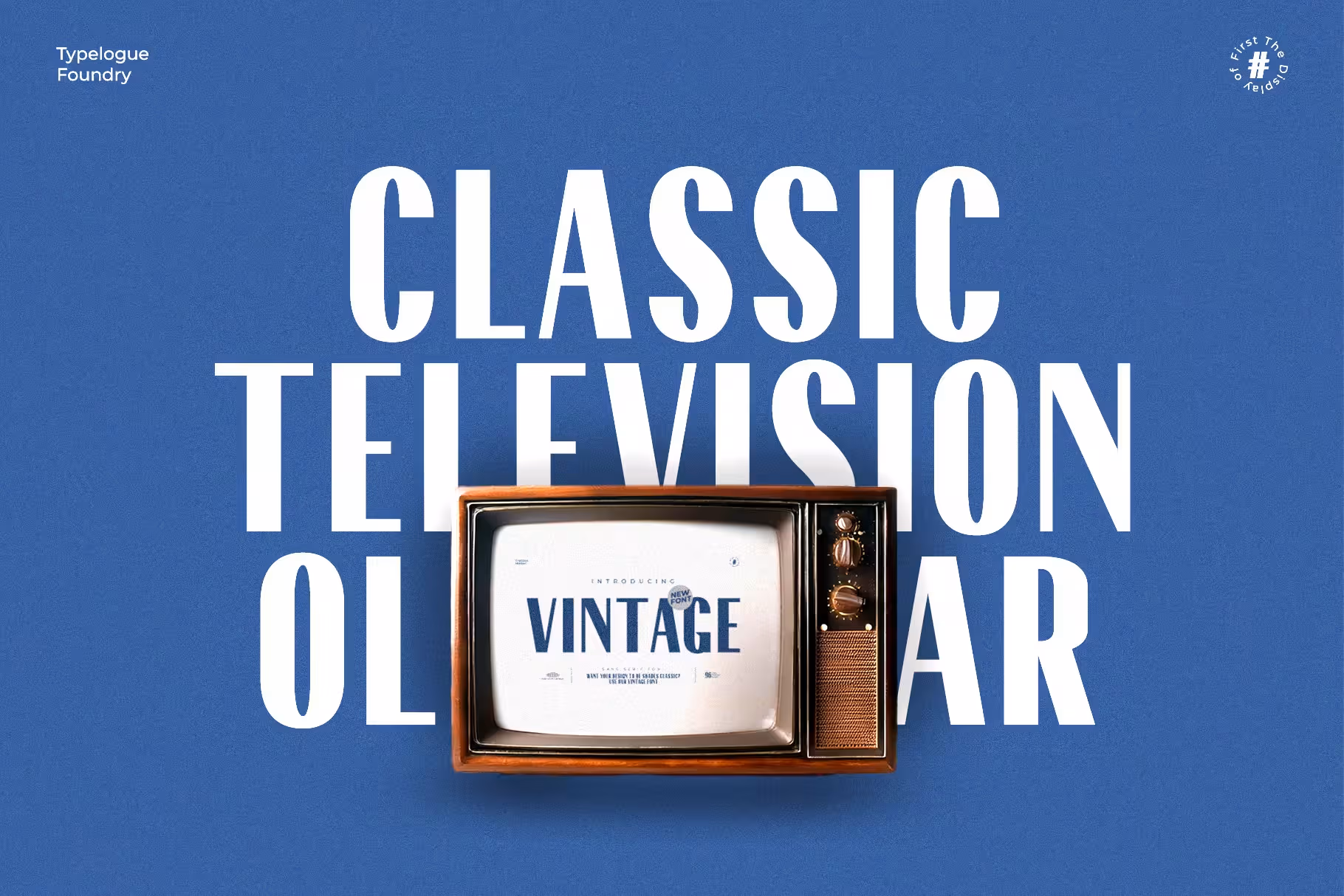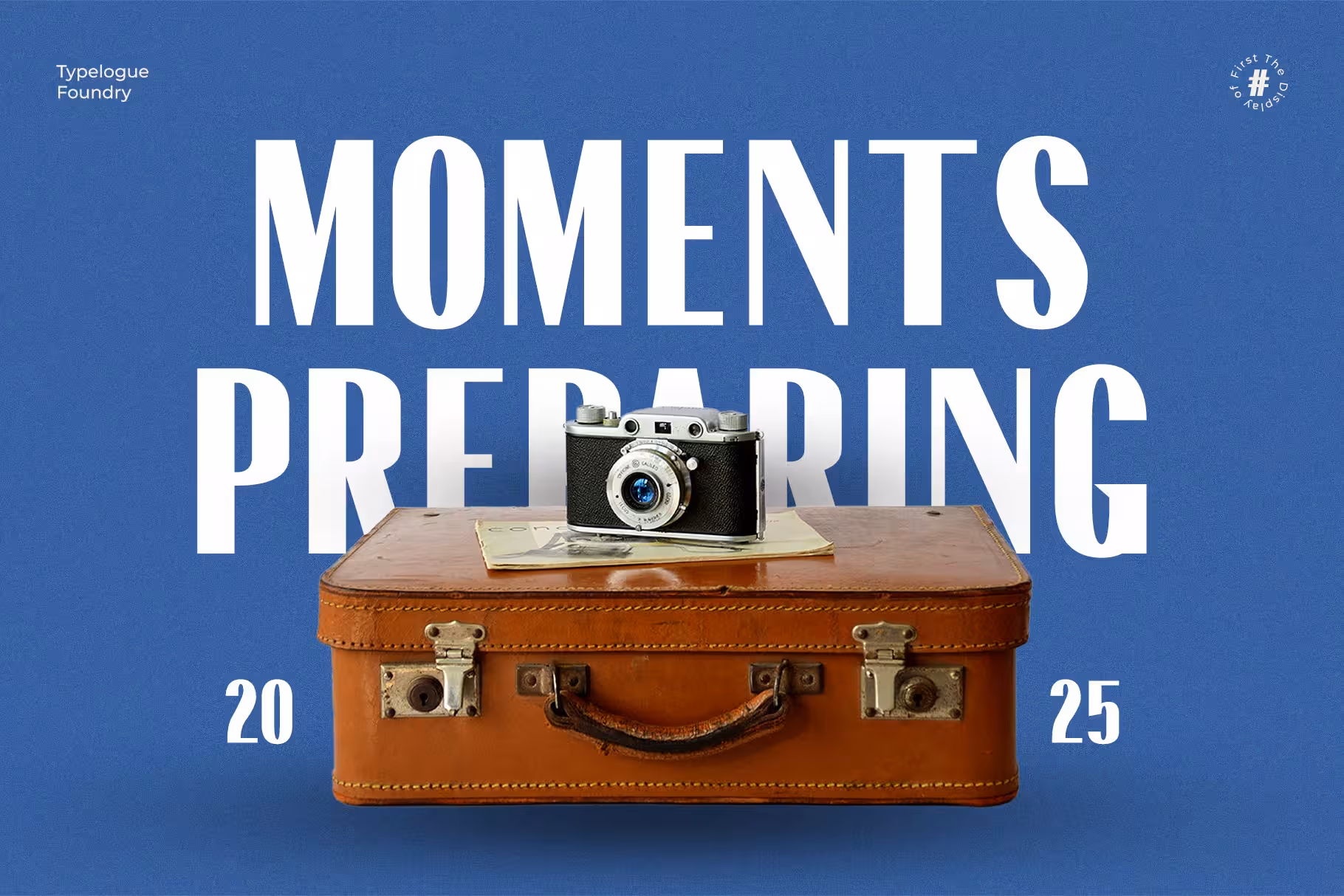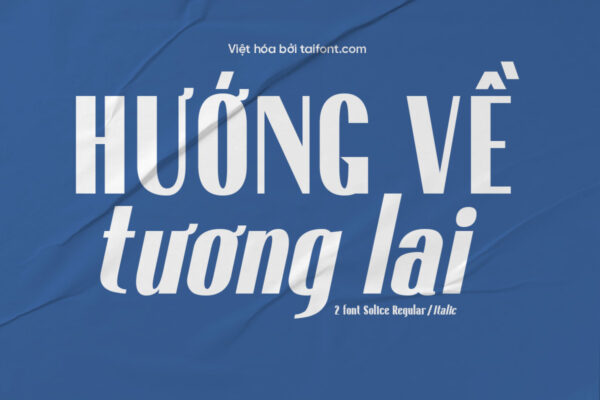
Giới thiệu về Font TF Solice Regular & Italic Việt hóa
TF Solice Regular & Italic Việt hóa là một bộ font chữ không chân (sans-serif) nổi bật với thiết kế mạnh mẽ, dứt khoát và đầy tinh tế. Với hai phiên bản Regular (thẳng) và Italic (nghiêng), bộ font này mang đến sự linh hoạt trong việc thể hiện thông điệp, toát lên phong thái chuyên nghiệp, hiện đại và đẳng cấp, lý tưởng cho mọi ấn phẩm cần sự rõ ràng và cuốn hút.
Với đặc điểm là nét không chân gọn gàng, tính thẩm mỹ cao và khả năng ứng dụng đa dạng, Solice là lựa chọn hoàn hảo cho các thiết kế muốn truyền tải sự hiện đại, mạnh mẽ và sự độc đáo, đặc biệt là trong lĩnh vực nội thất:
- Thiết kế tạp chí nội thất: Hoàn hảo để sử dụng cho các tiêu đề chính, lời dẫn, hoặc nội dung bài viết trong các tạp chí về kiến trúc, nội thất, thiết kế nhà cửa. Nét chữ mạnh mẽ của Solice giúp tăng tính trang trọng và dễ đọc, đồng thời tạo cảm giác cao cấp, thu hút độc giả.
- Thiết kế đồ dùng nội thất: Lý tưởng để sử dụng trên nhãn mác sản phẩm, catalogue, brochure của các thương hiệu nội thất, đồ gia dụng cao cấp. Font này giúp khẳng định chất lượng, sự sang trọng và vẻ đẹp tinh túy của sản phẩm, nâng tầm giá trị thương hiệu.
- Thiết kế nhận diện thương hiệu: Phù hợp cho logo, tagline hoặc bộ nhận diện thương hiệu của các công ty, doanh nghiệp trong ngành thiết kế, kiến trúc hoặc nội thất. Solice giúp xây dựng một hình ảnh thương hiệu vững chắc và dễ nhận diện.
- In ấn và quảng cáo: Đảm bảo khả năng đọc tốt ngay cả ở kích thước lớn, và tạo hiệu ứng thị giác mạnh mẽ khi in trên các chất liệu khác nhau như bảng hiệu, backdrop sự kiện hoặc các ấn phẩm quảng cáo.
Với TF Solice Regular & Italic Việt hóa, bạn có thể dễ dàng thổi hồn tinh tế, sang trọng và vẻ đẹp hiện đại vào các thiết kế, tạo ra những sản phẩm không chỉ đẹp mắt mà còn đầy cảm xúc và sức hút đặc biệt.